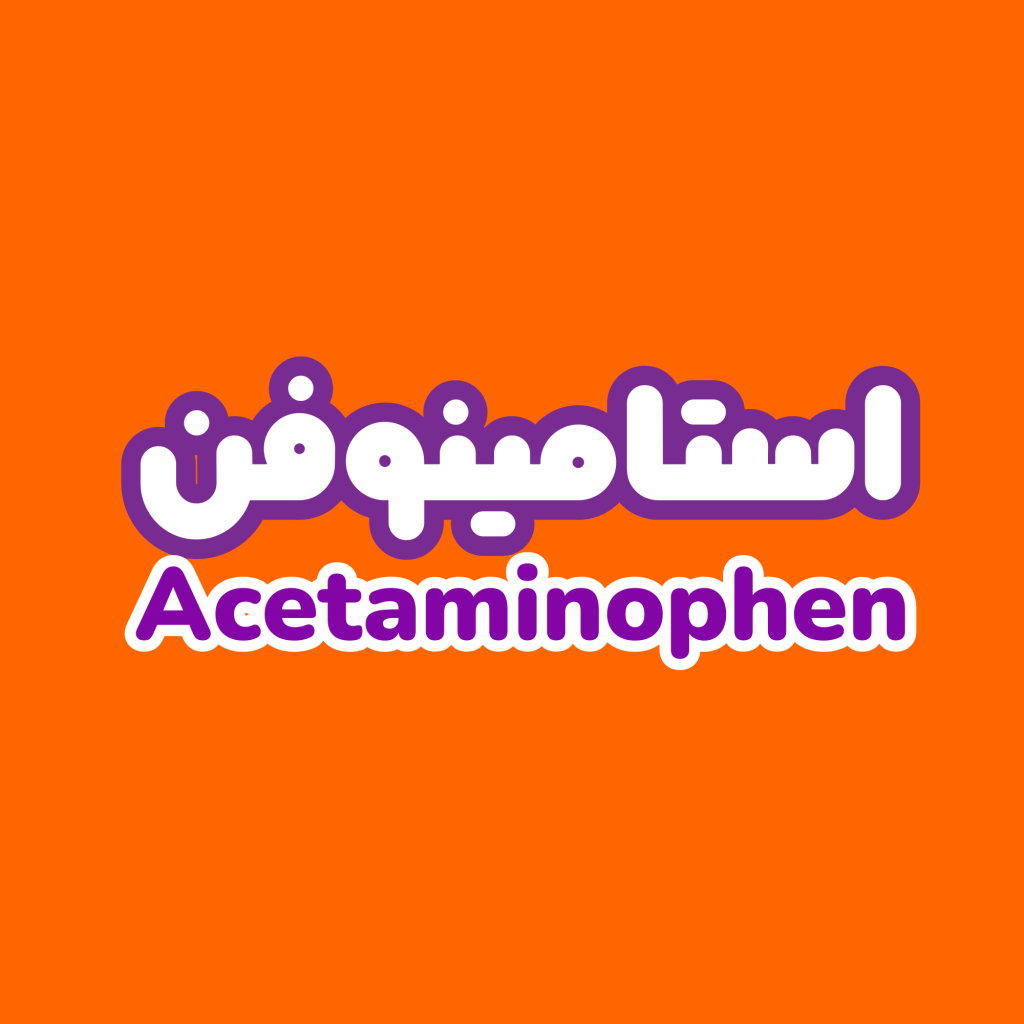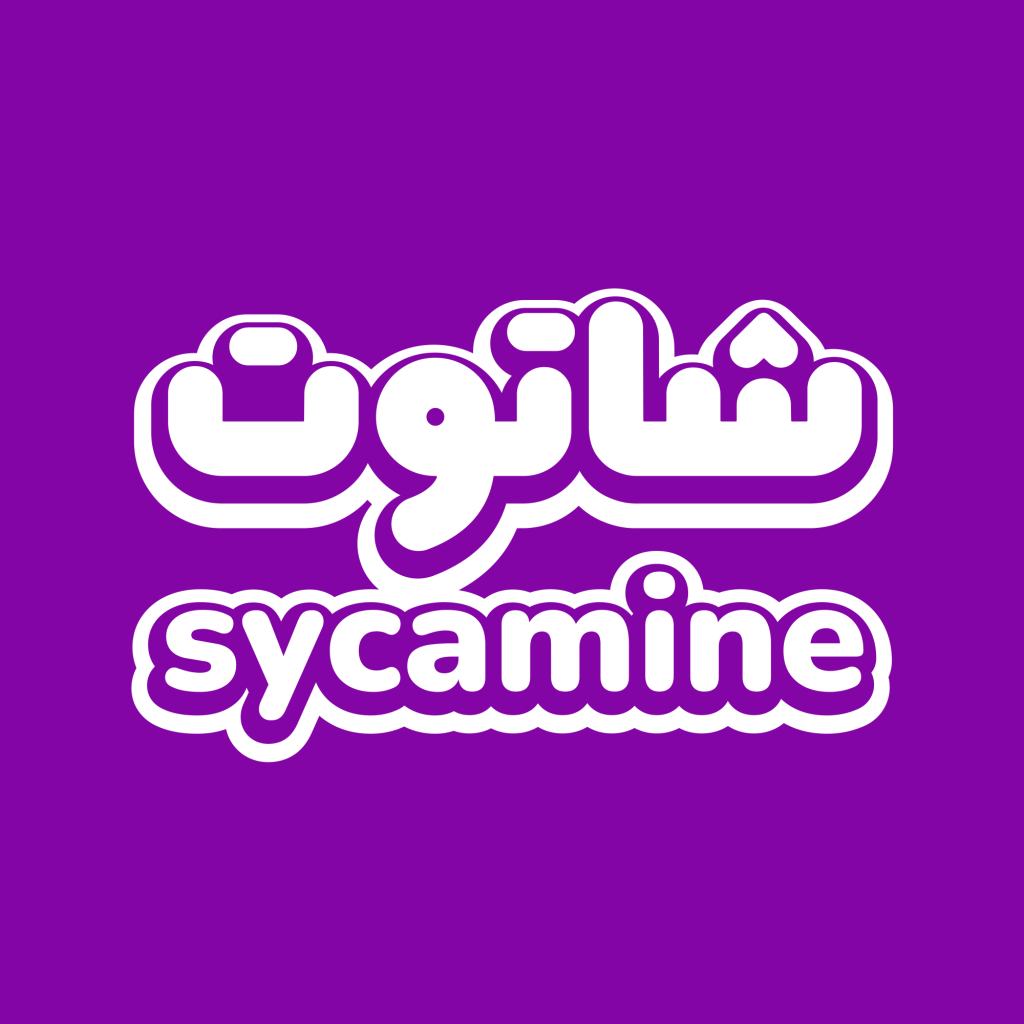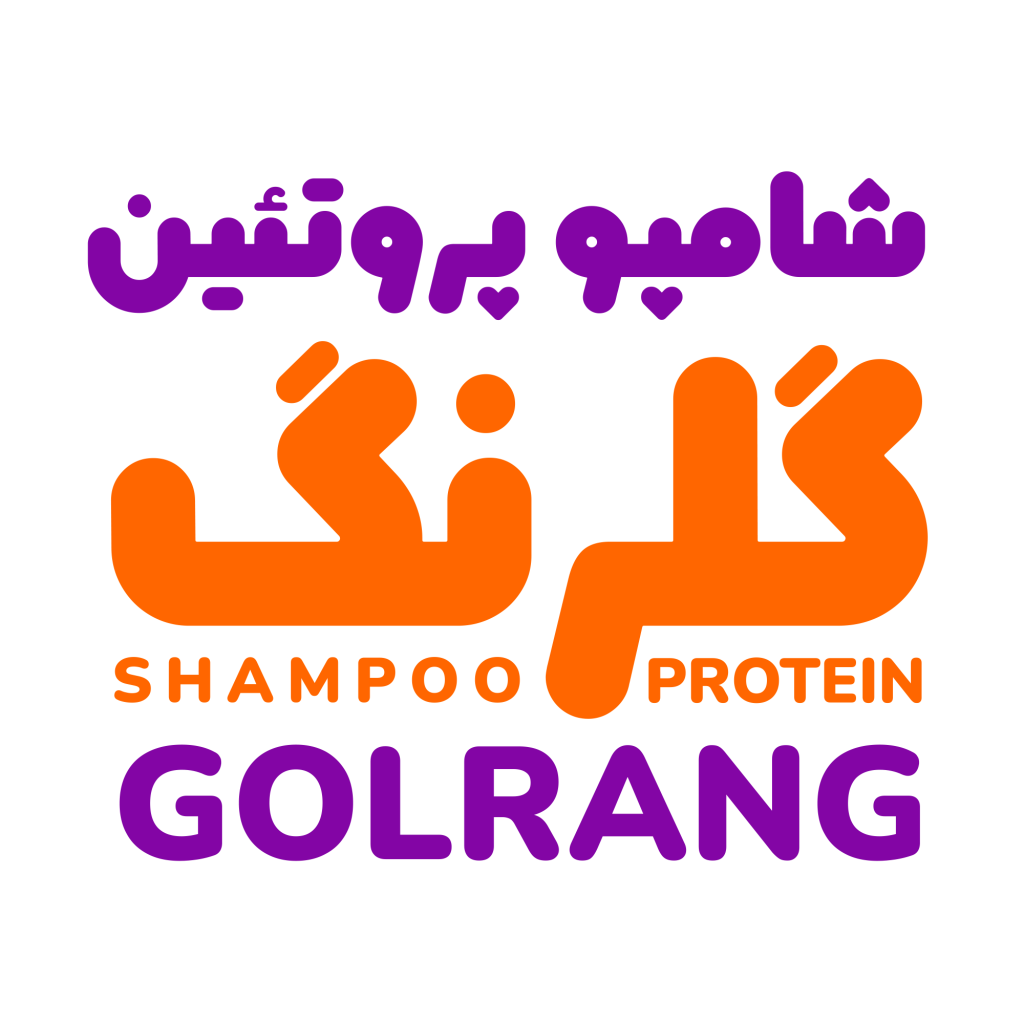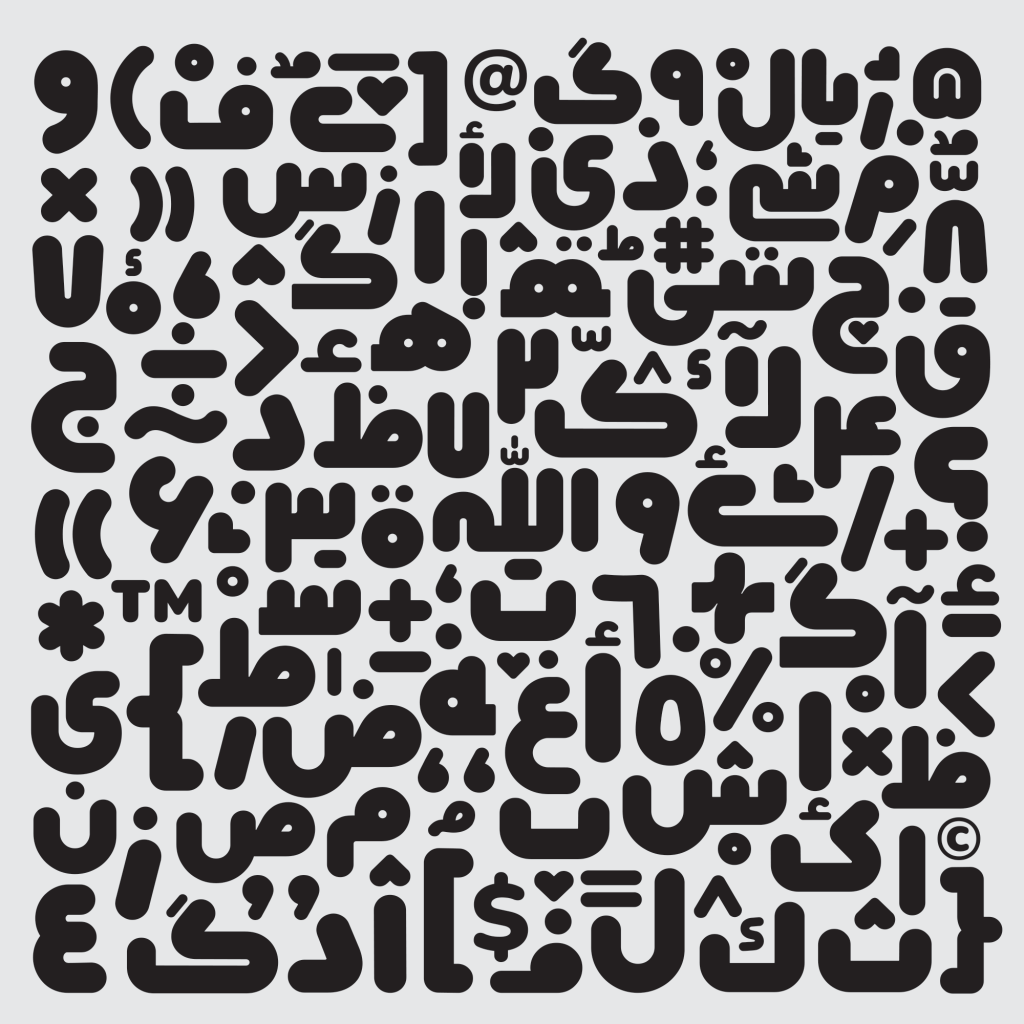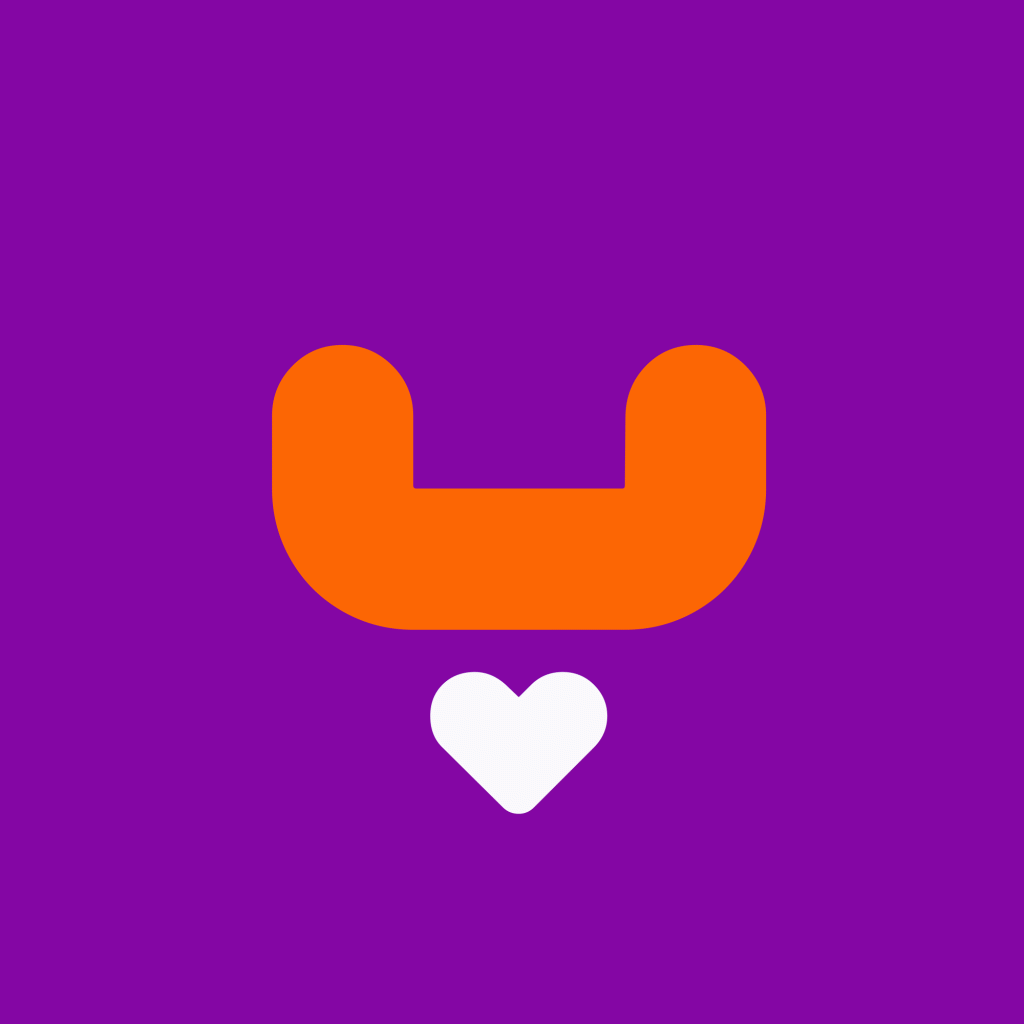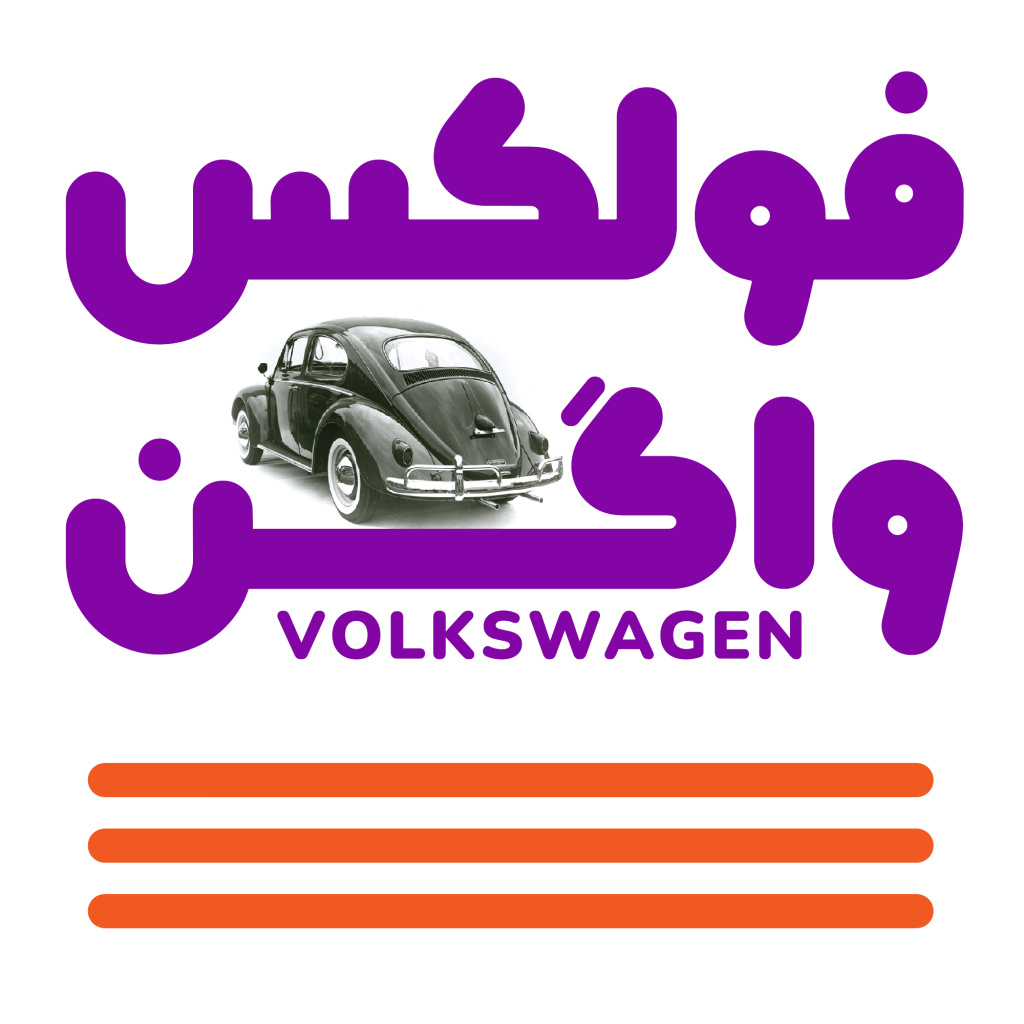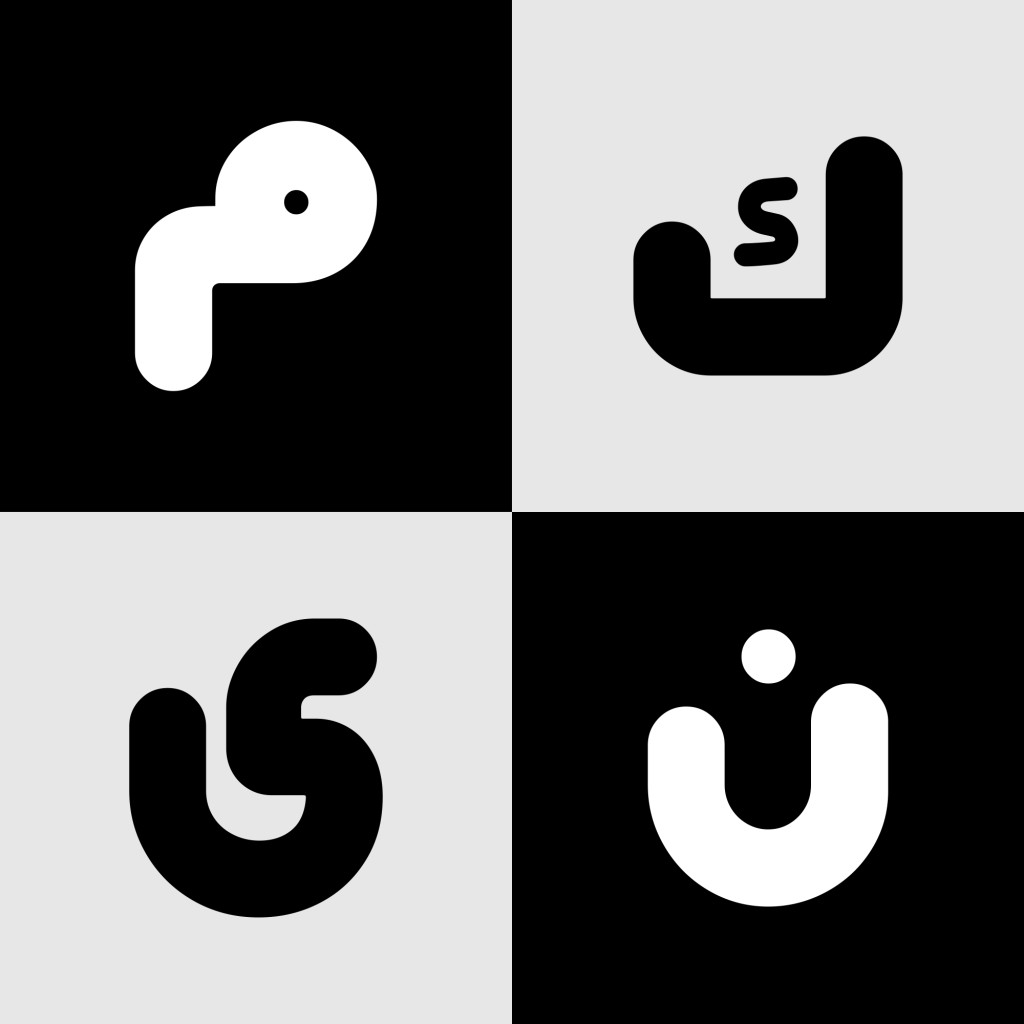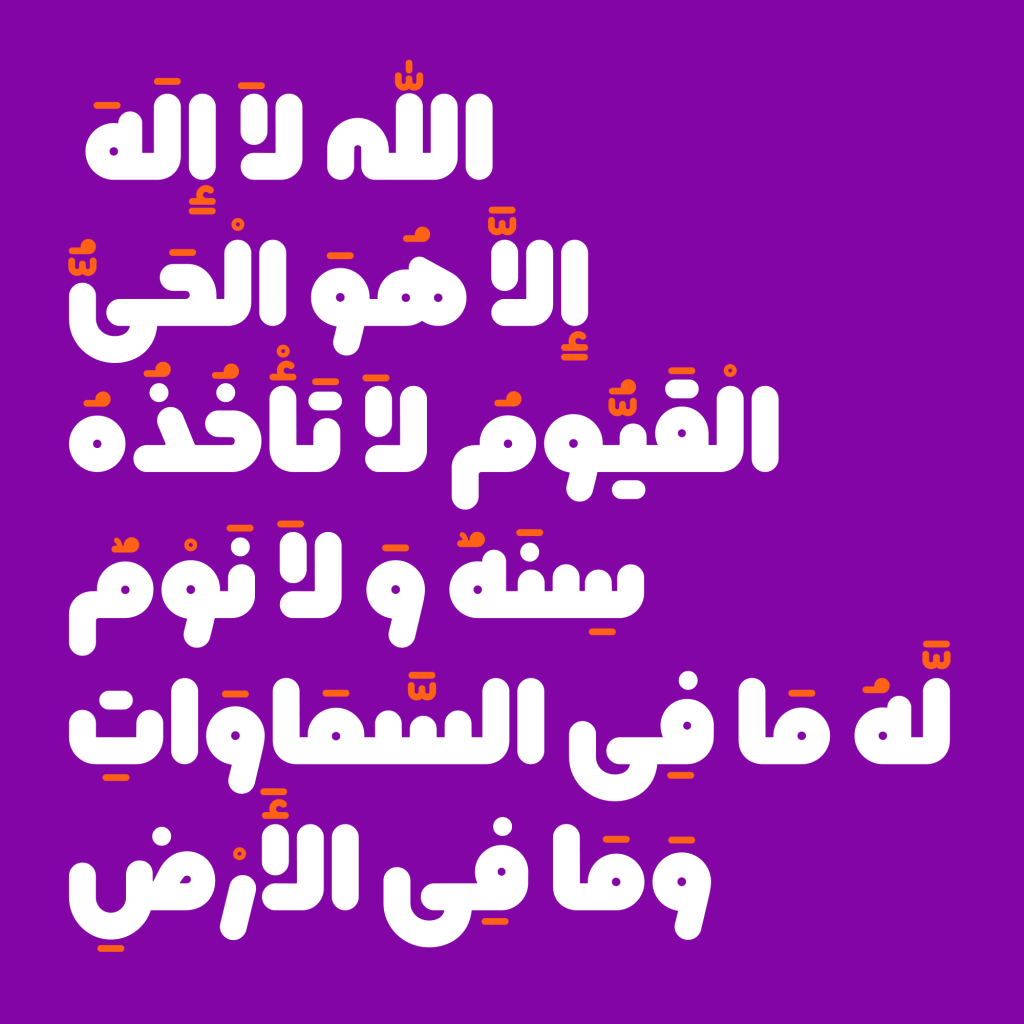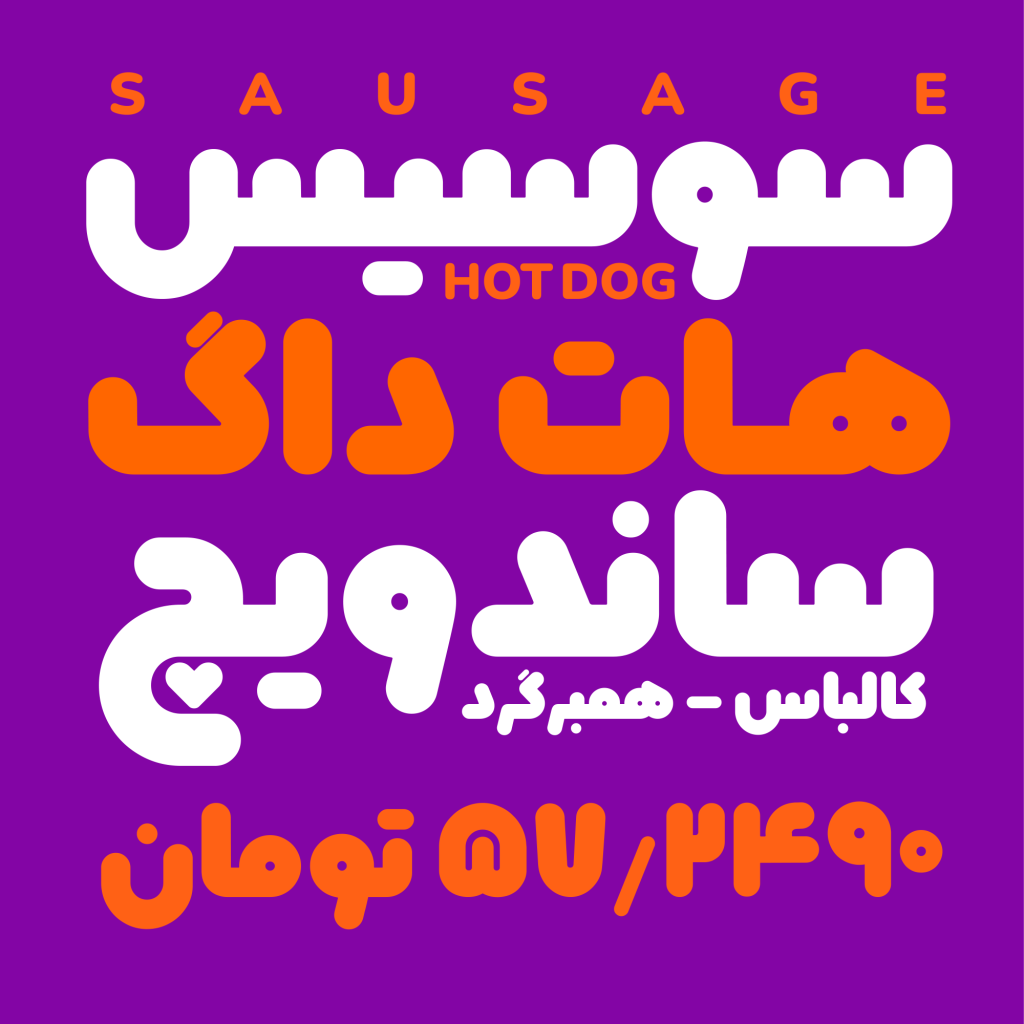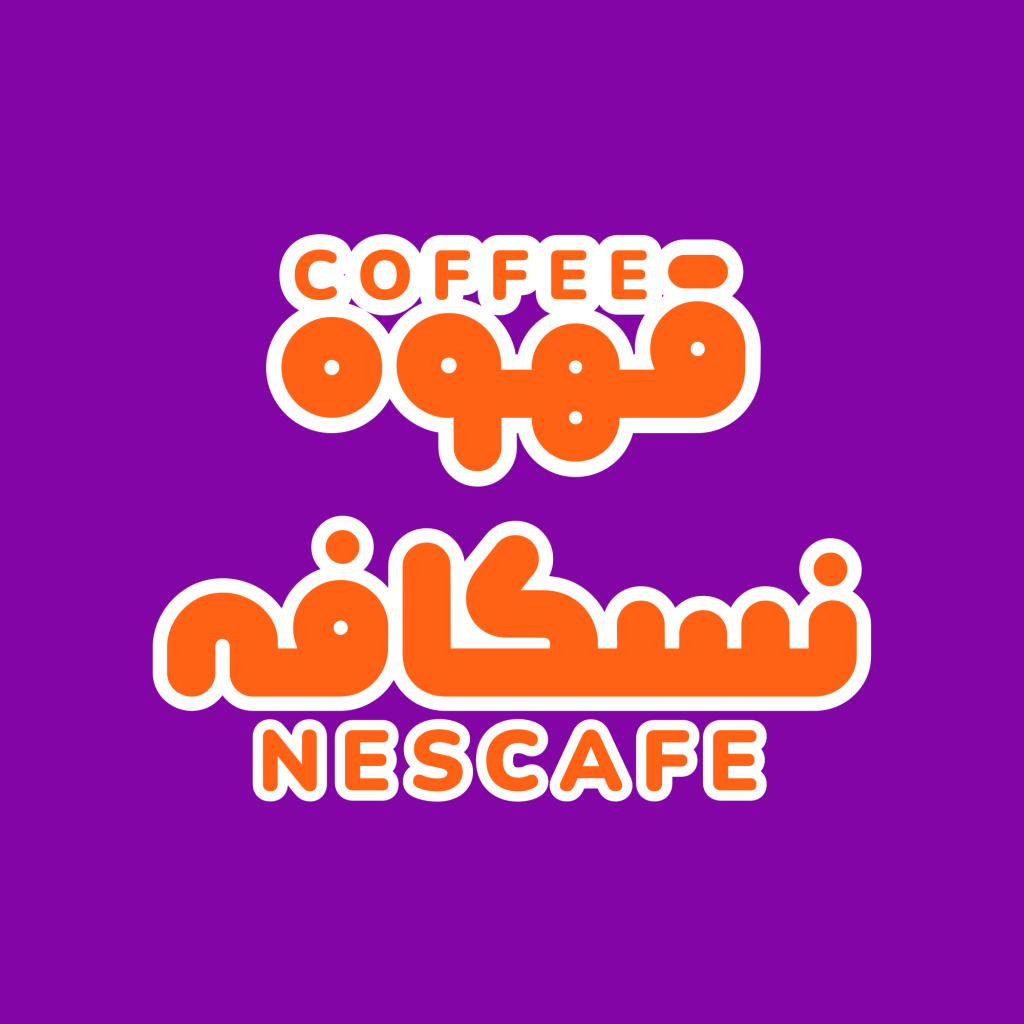
فونت کپسول قلمی فانتزی و پر انرژی
فونت کپسول با طراحی و هماهنگی شهرزاد اکبری و فرهود مقدم طراحی و ساخته شده است. کپسول ایده ای فانتزی داشته و با شخصیتی به روز و پویا و پرانرژی دارای کاربرد های خاص و ویژه است . از جمله این عرصه برای کاربرد آن می توان جهت موضوعات تجاری و مدرن مثل صنایع بسته بندی، عنوان فروشگاه، نشریات و کتاب های کودک و نوجوان ، برندهای تجاری و…. قابل استفاده است. از صنعت نشر و چاپ گرفته تا فضای دیجیتال و دنیای وب فضای کاری این قلم جذاب و مهیج است.
از ویژگی های ظاهری و فرم های طراحی این تایپ فیس میتوان به؛ مینیمال بودن، بامزه، نرم و لطیف، سنگین، تپل، مهربان، فانتزی و … اشاره نمود . به دلیل طراحی حروف و گلیف های این قلم با منحنی های نرم و متعادل و اجتناب از زوایای تند و تیز حس و احساس صمیمی و گرمی را به مخاطب منتقل می کند. ویژگی ظاهری نمایشی و تزئینی برای این قلم جزء ساختار جدایی ناپذیر آن به شمار می رود.
پشتیبانی کپسول از ترکیبات جایگزین
همه می دانیم وجود ترکیبات و حروف جایگزین در یک تایپ فیس علاوه بر افزایش جاذبه جلوه های بصری به یک فونت سبب ایجاد تنوع و پویایی در طراحی و نوشته ها می شود.
قلم کپسول از حروف جایگزین مانند: ” کـ ـکـ ـک ک ، گـ ـگـ ـگ گ، پـ ،بـ ، نـ ، یـ ، ئـ ، تـ ، و، ر، ژ،ز، ـهـ ، ـه، م، سـ، شـ ” بهره مند است . همچنین در این فونت حروف 3 نقطه، داری حالت های مختلف هستند مثل ژ، چ، ث، ش،پ که با استفاده از کلیدهای میانبر و استایل ستها قابل تغییر می باشند.
کپسول به لحاظ شخصیت و فرمی که دارد فقط برای نوشتن عبارات، کلمات و ترکیبهای مختصر کاربرد دارد و برای استفاده در متن و جملات طولانی توصیه نمیشود. فونت پارادوکس از نقطه نظر هم خانوادگی و شباهت به این تایپ فیس شباهت زیادی دارد. در زیر تصاویری از این قلم شاد و پر انرژی را به صورت نمونه برای شما دوستان قرار داده ایم می توانید جهت آشنایی بیشتر با نحوه طراحی فرم های حروف و لیگچر ها و سایر خصوصیات و … از این تصاویر دیدن فرمائید.
این فونت از زبان فارسی، عربی و انگلیسی پشتیبانی میکند.